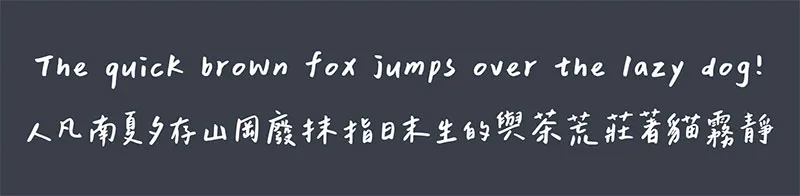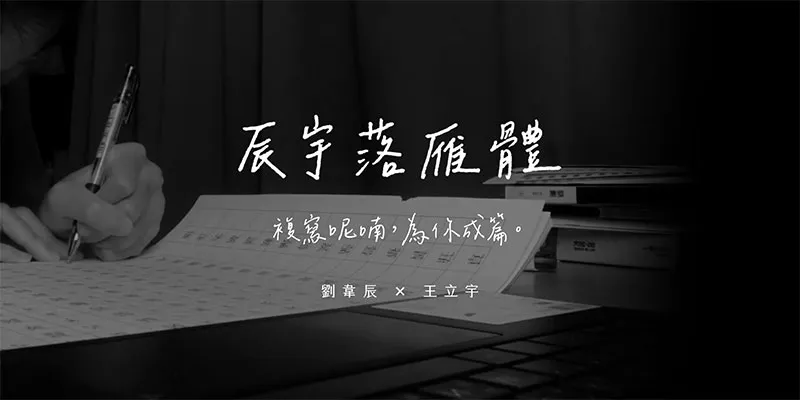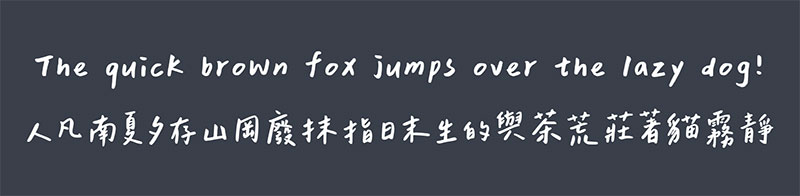
「辰宇落雁體」是我與韋辰在學校的自主學習計畫,由韋辰負責書寫,我進行後製而成。手寫字型就像是我們將字詞複寫於紙上,讓字跡留下,以這種近似雋永的形式封裝,使被複寫的日常沒有保質期,也像是一種永恆的召喚,在任何無法抵達的以後,都能為你書寫成篇。
製作故事
唉,你要不要做手寫字體?
去年的八月,那陣子我開始關注字體相關議題,在一次偶然看到韋辰的手寫字後,萌生出要是自己也能做一套手寫字體,真是太酷了!而適逢108課綱的我們,課綱強調自主學習的精神,正巧讓我們有機會發展計劃,於是,手寫字體的鑽研之路就這樣開始了⋯⋯
但「萬事起頭難」,我們一開始的起步並不這麼順利,對於字體不太熟悉的我們於是開始搜尋相關資訊,忽而地想到,YouTube頻道「壹加壹」與justfont推出的粒線體,我們寫信請教手寫字體的前期製作方向,獲得了他們真誠的回覆,他們向我們分享製作字體需注意的要點,也在計劃過程中提供我們諮詢與技術指導,成為很大的助力。
我們最初是在線上字體制作平臺──「守寫字網站」習得手寫字體的製作流程,後來為了更大程度的製作自由,我們嘗試拆解流程,並以自己的方式進行製作,然摸索的過程並非一蹴可及,在那段期間的每週四,我潛心鑽研的同時,韋辰就在一旁書寫,兩個人窩在圖書館的角落為心中的理想並肩努力著,製作字體是枯燥的,日復一日的書寫、修改與後製,現在想想,我們還挺浪漫的,為了完成理想,不惜代價的繞了點路,也有好幾次洩氣的想著,或許真的做不出來了,是對於成果的想像才讓我們堅持下來。
在字體做出成果後,也陸續獲得不少稱讚,神奇的是,製作過程中並未覺得特別的我們,在第一次打出完整的句子時,卻被感動了。若浪漫一點來說,製作手寫字體這件事,似將字詞複寫於紙上,將字跡留下為人使用。
回想製作的契機,那句「唉,你要不要做手寫字體?」在今天終於實現了,韋辰寫下這些文字後也將與十六歲告別,正所謂字如其人,期望她未來回首,能在字裡行間看見自己。
其他可能
其實,我們在計劃一開始製作的字體是以Pentel Touch書寫的粗體字,但因為製作目標與後期調整較為複雜,在稿紙書寫完成後,遲遲未能釋出字體。而我們隨後也製作了原子筆書寫的版本,也就是現在的「辰宇落雁體Thin」。
上圖為Pentel Touch版本字樣,預計於2023年開始製作。